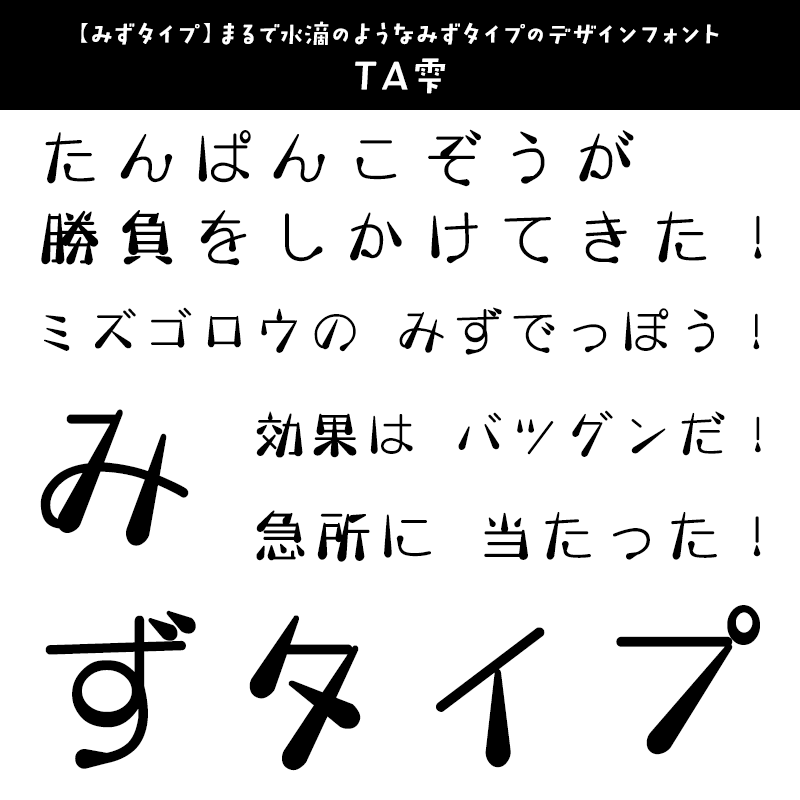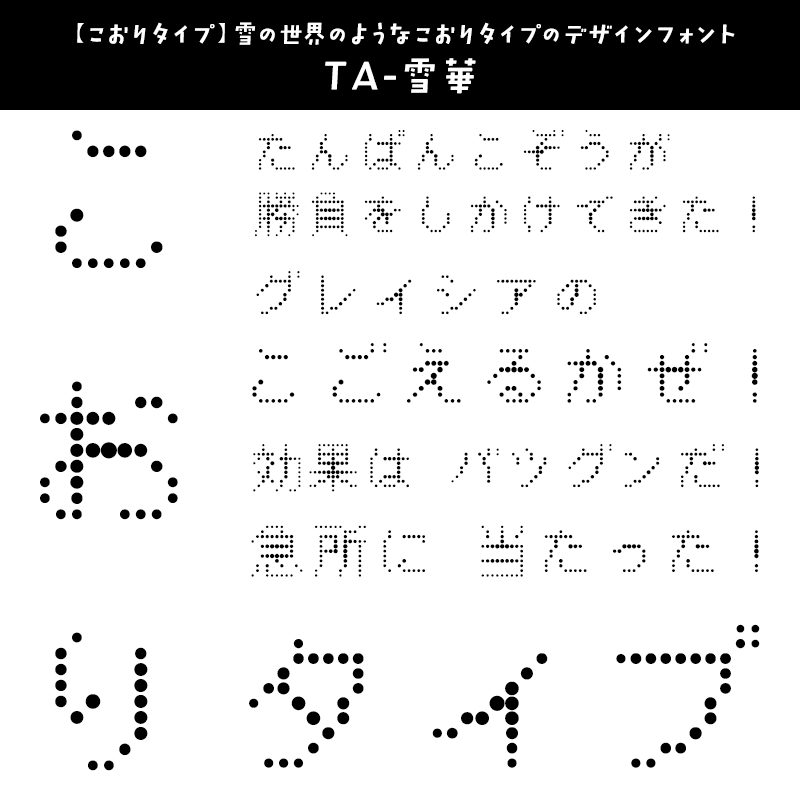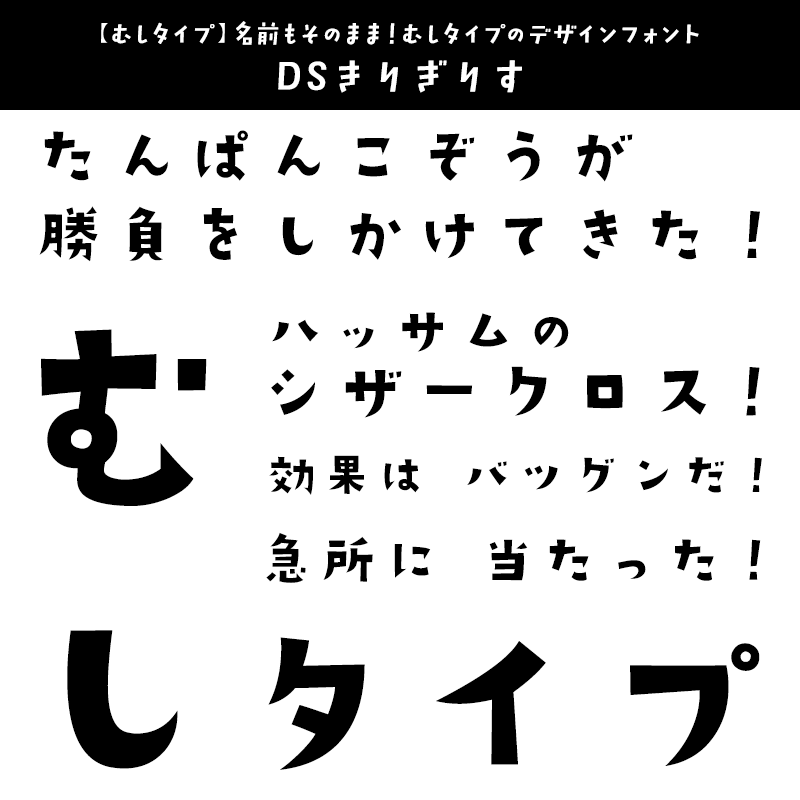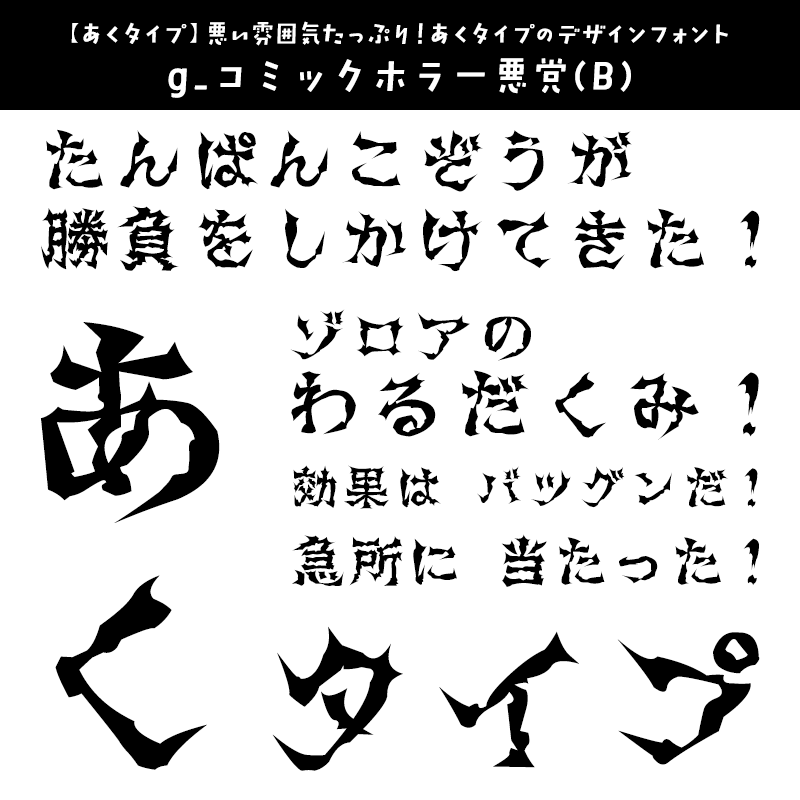
「ポケモン」に合うフォントをスタッフが選びました
「ポケモン」に合うフォント ノーマルタイプ
【ノーマルタイプ】クセの少ないノーマルタイプなゴシック体
エヌユー太角ゴシック【CFONT】
「ポケモン」に合うフォント 大髭
どっしりとした男前のフォントをイメージして作成されたゴシック体。ひらがな、カタカナは少しポップなフォルムのデザインです。シンプルで特定の属性をもたないノーマルタイプのポケモンにぴったりのフォントです。
「ポケモン」に合うフォント ほのおタイプ
【ほのおタイプ】荒々しく力強いほのおタイプの筆文字フォント
横丁&鍛所 ファイトフォント【六葉情報】
「ポケモン」に合うフォント 横丁&鍛所 ファイトフォント
ファイトフォントは、勢いのあるはらいが特徴的な極太の毛筆書体で、荒々しく力強い印象を持っています。炎のような激しさが、火を操るほのおタイプにぴったりのフォントです。
「ポケモン」に合うフォント みずタイプ
【みずタイプ】まるで水滴のようなみずタイプのデザインフォント
TA雫【スキルインフォメーションズ】
「ポケモン」に合うフォント TA雫
その名の通り雫のようなデザインが特徴的なデザインフォント。水生生物の姿をしたみずタイプのポケモンにぴったりのフォントです。
「ポケモン」に合うフォント でんきタイプ
【でんきタイプ】ビリビリ!でんきタイプのデザインフォント
TA激震【スキルインフォメーションズ】
「ポケモン」に合うフォント TA激震
その名の通り激しさを感じる荒々しい手書き風フォント。ビリビリする電気を自在に操るでんきタイプのポケモンにぴったりのフォントです。
「ポケモン」に合うフォント くさタイプ
【くさタイプ】つるがクルクルとしたくさタイプのデザインフォント
TA-つるまる【FONT1000】
「ポケモン」に合うフォント TA-つるまる
その名の通り植物の「つる」のようにすらっと伸びた細身のデザイン、丸くからまるエレメントが特徴的。植物のような姿をしたくさタイプのポケモンにぴったりのフォントです。。
「ポケモン」に合うフォント こおりタイプ
【こおりタイプ】雪の世界のようなこおりタイプのデザインフォント
TA-雪華【FONT1000】
「ポケモン」に合うフォント TA-雪華
円を外側は小さく、内側にいくにつれ大きくすることで、雪のような印象を持つドットフォント。植氷や雪をモチーフにしたこおりタイプのポケモンにぴったりのフォントです。
「ポケモン」に合うフォント かくとうタイプ
【かくとうタイプ】闘争心にあふれるかくとうタイプの筆文字フォント
闘龍書体【昭和書体/コーエーサインワークス】
「ポケモン」に合うフォント 闘龍書体
闘争心にあふれ、力がありあまった若い龍が、空を舞うさまをイメージして作られた筆書系デザイン書体。ムキムキ筋肉、物理アタッカー型のかくとうタイプのポケモンにぴったりのフォントです。
「ポケモン」に合うフォント どくタイプ
【どくタイプ】凶悪そうな外見のどくタイプの筆文字フォント
DF大河体【ダイナフォント】
「ポケモン」に合うフォント DF大河体
起筆や払いの勢い、豪快かつ極太、筆文字ならではの勢いや力強さを表現した女性書道家による毛筆系書体。凶悪そうな外見のどくタイプのポケモンにぴったりのフォントです。
「ポケモン」に合うフォント じめんタイプ
【じめんタイプ】「じしん」のような破壊力!じめんタイプのゴシック体
DFひびゴシック体 W14【ダイナフォント】
「ポケモン」に合うフォント DFひびゴシック体 W14
ひびゴシック体は、超極太ゴシック体をベースに、筆画の一部に切り込みを入れたインパクトあるデザイン。強力技の「じしん」を使えるじめんタイプのポケモンにぴったりのフォントです。
「ポケモン」に合うフォント ひこうタイプ
【ひこうタイプ】軽やかに舞う!ひこうタイプの明朝体
DSそよ風【七種泰史/デザインシグナル】
「ポケモン」に合うフォント DSそよ風
明朝タイプの軽やかなデザインフォント。はらいやハネのデザインのような軽やかな動きを持ったひこうタイプのポケモンにぴったりのフォントです。
「ポケモン」に合うフォント エスパータイプ
【エスパータイプ】不思議なフォルム!エスパータイプのデザインフォント
TA-方縦K500【FONT1000】
「ポケモン」に合うフォント TA-方縦K500
すべての字画が水平、垂直、45度だけでデザインされ字画のラインがそろうことで、科学的な印象を与える造形に仕上がるロゴタイプフォント。SFっぽいデザインがエスパータイプのポケモンにぴったりのフォントです。
「ポケモン」に合うフォント むしタイプ
【むしタイプ】名前もそのまま!むしタイプのデザインフォント
DSきりぎりす【七種泰史/デザインシグナル】
「ポケモン」に合うフォント DSきりぎりす
切り文字のような大胆さを持った一番人気のデザイン書体。先端がとがったフォルムがむしタイプのポケモンにぴったりのフォントです。
「ポケモン」に合うフォント いわタイプ
【いわタイプ】岩石のような堅さを持ったいわタイプのデザインフォント
DSストロング【七種泰史/デザインシグナル】
「ポケモン」に合うフォント DSストロング
見出しやキャッチコピーにぴったり。岩石のような堅さ、力強さの中にも優しさを感じる、太く元気な書体。まさに岩のようなフォルムがいわタイプのポケモンにぴったりのフォントです。
「ポケモン」に合うフォント ゴーストタイプ
【ゴーストタイプ】ホラー感あふれるゴーストタイプの古印体
g_コミック古印体-フルセット B 太字【よく訓練されたフォント屋】
「ポケモン」に合うフォント g_コミック古印体-フルセット B 太字
コミックのホラーシーンのセリフに使用することを想定して作成された古印体風の手書き文字フォント。怖い雰囲気を持つゴーストタイプのポケモンにぴったりのフォントです。
「ポケモン」に合うフォント ドラゴンタイプ
【ドラゴンタイプ】豪快さNo.1の力強くインパクト溢れる毛筆書体
豪龍書体【昭和書体/コーエーサインワークス 】
「ポケモン」に合うフォント 豪龍書体
豪快な毛筆の力強さ及びかすれを最大に活かしたインパクトある高解像度毛筆書体です。その名の通り龍のような豪快さが、ドラゴンタイプのポケモンにぴったりのフォントです。
「ポケモン」に合うフォント あくタイプ
【あくタイプ】悪い雰囲気たっぷり!あくタイプのデザインフォント
g_コミックホラー悪党(B)【よく訓練されたフォント屋】
「ポケモン」に合うフォント g_コミックホラー悪党(B)
同作者の「g_コミックホラー恐怖(R)」をもとに、より禍々しく物騒で恐ろしげに存在感を強めた太字版ホラーフォントです。悪人、邪悪さ、険悪さ、嘲笑感など、あくタイプのポケモンにぴったりのフォントです。
「ポケモン」に合うフォント はがねタイプ
【はがねタイプ】鋼のような硬さ!はがねタイプのデザインフォント
金剛書体【昭和書体/コーエーサインワークス】
「ポケモン」に合うフォント 金剛書体
遊び心の入った昭和デザイン書体シリーズのデザイン書体。「金剛⇒ダイアモンド⇒硬い」をイメージして仕上げたインパクト抜群の書体。硬質なイメージがはがねタイプのポケモンにぴったりのフォントです。
「ポケモン」に合うフォント フェアリータイプ
【フェアリータイプ】キュートでかわいいフェアリータイプのデザインフォント
TA-アンダンテ【FONT1000】
「ポケモン」に合うフォント TA-アンダンテ
文字自体のバランスをあえて崩しつつも文章にするとバランスを取り合い、楽しい印象を与えるフォントです。フェアリータイプのポケモンにぴったりのフォントです。